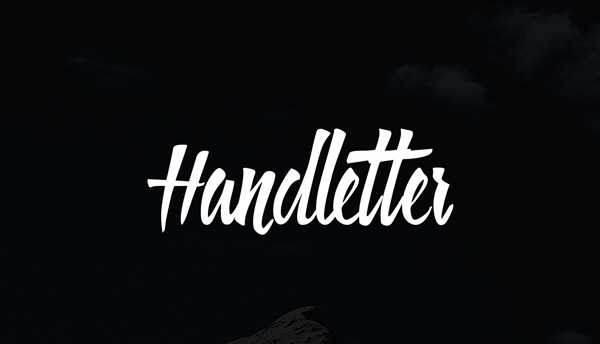
Os dejo una tipografía que me ha encantado con un rollo muy fresco y actual. Con cierto enfoque urbano que podrá serviros para muchos diseños con un enfoque joven. La licencia es libre así que podéis utilizarla tanto para proyectos personales como comerciales. Para descargarlo pulsad sobre la imagen o en el link del pie de la entrada. Espero que os sirva y recordad que los like y los follow ayudan mucho así que visitadnos en Twitter y Facebook. También nos podéis encontrar en Flipboard buscando nuestra revista El Arquitecto de Ilusiones.